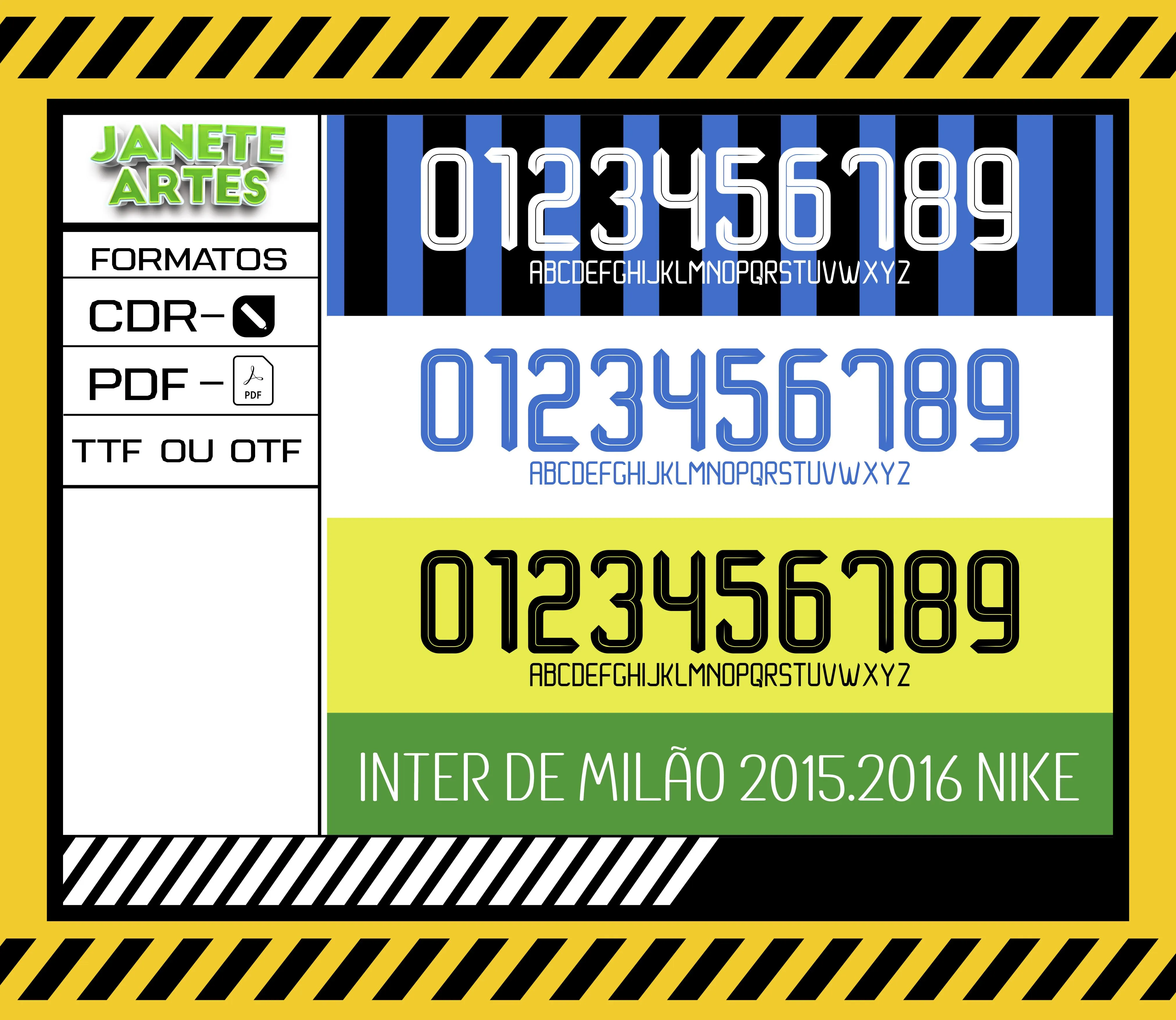
Fonte de Time Tipografia Inter de Milão 2015 - 2016
Confira a Fonte de Time Tipografia Inter de Milão 2015 - 2016, um arquivo digital exclusivo em CDR para personalizar camisetas com um design clássico e marcante. Perfeito para fãs e eventos especiais.
Uma história de paixão pelo futebol e design
Imagine João, um torcedor fanático do Inter de Milão, que queria criar algo único para os jogos da temporada 2015-2016. Ele buscava uma forma de mostrar seu amor pelo time com estilo e autenticidade. Ao encontrar a Fonte de Time Tipografia Inter de Milão 2015 - 2016, João pôde personalizar camisetas que encantaram seus amigos e tornaram-se o destaque nas arquibancadas. A emoção de vestir uma peça com aquele design fiel ao histórico do time trouxe uma conexão maior com as vitórias e desafios daquela temporada inesquecível.
• O que é exatamente este produto? É um arquivo digital da fonte tipográfica usada pelo Inter de Milão na temporada 2015-2016.